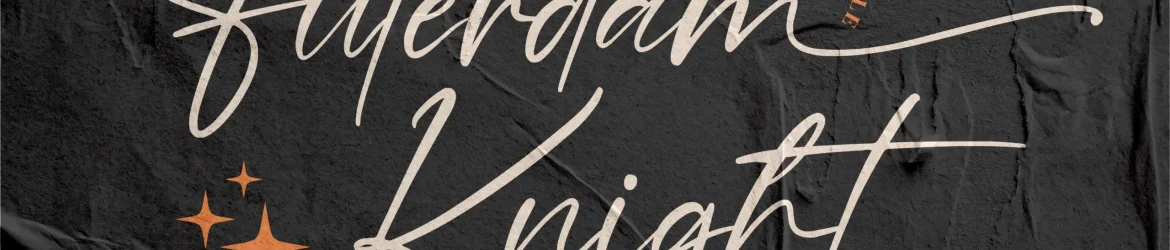
Futerdam Knight Font – Download Grátis
Esta é uma fonte de firma premium perfeita para qualquer projeto que você possa imaginar, desde logomarcas, projetos de marcação até a embalagem de produtos e pacotes. Seja um manto personalizado, uma citação ou uma cartela de cores, a Futerdam Knight se adequa a eles sem problema. Não importa o tipo de arte que você deseje criar, seja para objetos domésticos como chávenas ou sacolas de shopping, até materiais mais sofisticados como nomes de cartão, convites de aniversário ou selos personalizados; esta fonte trará um toque de elegância e uma sensação premium. Seja você um fotógrafo que precisa de um toque único em suas imagens, tenha a necessidade de adicionar um design sofisticado à sua marca ou estampar sua própria identidade visual em diferentes materiais com essa fonte de firma, sempre garantindo o mesmo grau de qualidade e refinamento.